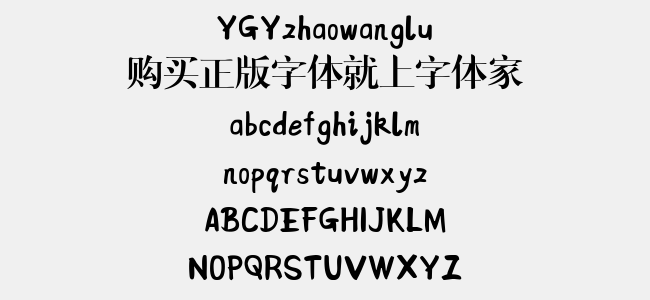
YGYzhaowanglu
字体作者:YGY-ywtixi
字体名称:YGYzhaowanglu
字体字数:26个英文大小写字母及和阿拉伯数字
字体家族:YGY-ywtixi
书体类型:英文类
字体作者:YGY
YGYzhaowanglu
YGYzhaowanglu是一款个性独特的英文字体,由YGY-ywtixi制作发布,非常适合创意类的PS字体,英文广告设计载体上使用,在设计中选择这款字体应用的话,会起到非常理想的效果。
YGYzhaowanglu - 大写字母/小写字母/数字